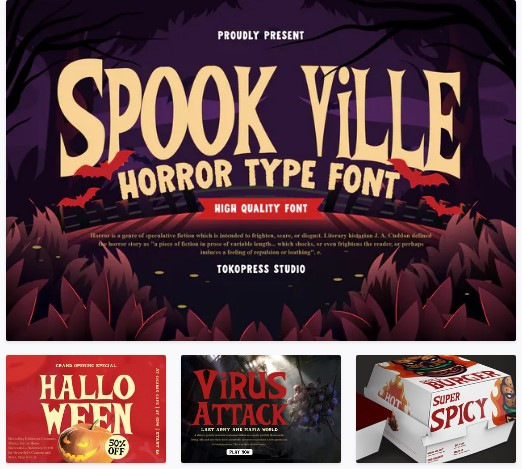
Название: Spook Ville Font (2021)
Spook Ville - страшный шрифт
Сова улюлюкает, дует ледяной ветер, волки воют.... и вы слышите приближающийся царапающий звук. Это все ужас и страх в Spook Ville.
Отлично подходит для аудитории рынка таинственных игр, плаката на Хэллоуин, названия фильма, меню веселого ресторана/кафе, журнала, обложек youtube, миниатюр youtube, обложек страниц социальных сетей и так далее...
Основные латинские буквы A-Z и a-z, цифры, пунктуация
Кодированные символы PUA